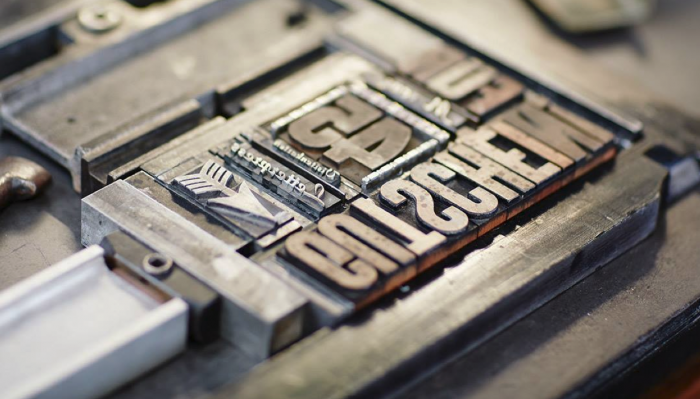
hatte die Möglichkeit mit ein paar alten (ca. 100 Jahre) Holzletter zu drucken.
Sofort verliebt in die Technik und den Look auf Munken Papier.
ICH MÖCHTE GERN MEHR ZUM THEMA »Holzdruck« WISSEN, leider ergab die Forensuche nicht viel.
Gern etwas über die Geschichte (gern auch in Deutschland) über die Technik, vielleicht eine gute Doku (youtube), was macht die Holzdruckkunst heute? usw.
Holzbuchstabenfräse im Museum der Arbeit in Hamburg:
ICH MÖCHTE GERN MEHR ZUM THEMA »Holzdruck« WISSEN, leider ergab die Forensuche nicht viel.
… was macht die Holzdruckkunst heute?
Es gibt (vom Holzschnitt abgesehen, um den es Dir ja gerade nicht geht) keine »Holzdruckkunst«. Es gibt Buchdruck, und wenn die Schriftgrade zu groß werden, um sinnvoll in Blei gegossen und gelagert werden zu können, wurden sie halt in Holz geschnitten. Holzdruck ist also keine eigene Disziplin, nicht mal eine abgrenzbare Untergruppe des Buchdruckes, Holz- und Bleibuchstaben wurden ja in derselben Druckform verwendet. Mit der Suche nach Holzdruck, Holzdruckkunst, Holzdruckerei etc. bist Du also, wenn mir das kalauern gestattet sei, immer auf dem Holzweg.
Jedenfalls hierzulande ist es so, wie Pachulke beschreibt. Meine Holzlettern kommen zum Einsatz, wenn der Zweck es fordert. Es gibt allerdings in Amerika Plakatshops, die drucken fast ausschließlich von Holzlettern, die haben gar keine anderen Schriften. Aber eine Website dazu fällt mir auf Anhieb nicht ein.
Es gibt allerdings in Amerika Plakatshops, die drucken fast ausschließlich von Holzlettern, die haben gar keine anderen Schriften.
Ich meine mich zu erinnern, daß hier letztens jemand einen Film aus einem dieser Läden gezeigt hat.
Zum Thema „Holzdruck“ sei ergänzend hinzugefügt, dass vor der Erfindung bzw. Weiterentwicklung des Buchdrucks durch Gutenberg sogenannte Blockbücher hergestellt wurden.
Von Holzstöcken gedruckte Bücher. Nicht nur die Bilder, sondern auch die Texte wurden in Holz geschnitten.
Blockbücher waren das Bindeglied zwischen den Handschriften und des Buchdrucks.
In China hatte man dieses Verfahren einige Jahrhunderte vorher entwickelt.
Es ist auch möglich, dass die Holzplatten in Teile zerschnitten, z. B. in einzelne Wörter oder Buchstaben und neu zusammengesetzt wiederverwendet wurden. So gesehen könnte hier auch eine Urform der beweglichen Letter entstanden sein.
Die Website zur Holzlettern-Sammlung von Rob Roy Kelly:
Hier ein paar Bilder von einem Workshop mit der Holzbuchstabenfräse im Museum der Arbeit in Hamburg:
Neue Holzbuchstaben kann man übrigens auch ohne Holzbuchstabenfräse herstellen. In der Holzwerkstatt der Muthesius-Kunsthochschule haben wir neulich ein komplettes Alphabet an der CNC-Fräse hergestellt.
Google mal Hamilton Woodtype Museum ...
habe mir jetzt ein paar eigene holzletter bestellt. der platzhirsch bei den üblichen gebraucht/DIY-plafformen scheint »vintage-letterpress« zu sein.
um nicht alle letter einzeln nacheinander zu drucken habe ich meist den block mit tesa fixiert. habt ihr da noch tipps? bzw. wo ich so ein vorrichtung herbekomme? (bild)
habe mir jetzt ein paar eigene holzletter bestellt. der platzhirsch bei den üblichen gebraucht/DIY-plafformen scheint »vintage-letterpress« zu sein.
Das ist nicht der Platzhirsch, sondern es sind erbarmungslose Geschäftemacher, die jede Letter einzeln völlig überteuert verkaufen, damit natürlich komplette Sätze auseinanderreißen und somit alles tun, um den Druck mit Holzlettern in Zukunft noch schwerer zu machen.
um nicht alle letter einzeln nacheinander zu drucken habe ich meist den block mit tesa fixiert. habt ihr da noch tipps? bzw. wo ich so ein vorrichtung herbekomme?
Empfehlenswert wäre ein Praktikum bei jemanden, der Ahnung davon hat und sowas macht. Sonst wirst du mit der Fragestellerei hier gar nicht mehr fertig ... Als Minimum wäre zumindest mal der Besuch bei einem Buchdrucker, einem Buchdruckmuseum oder einer Buchdruckwerkstatt anzuraten oder auch ein Blick in ein diesbezügliches Fachbuch beispielsweise
Hochdruck von Hans J. Wolfsturm und Hermann Burkhardt (1997).
Vom Platzhirsch habe ich mal eine fachkundige Antwort erhalten: Als ich ihn fragte, ob bei dem A einer seiner angebotenen Leichenteile zufällig De Little York auf Ober- und/oder Unterseite zu lesen ist, meinte er: »Ja, die machen tolle Schriften, oder?« (Anmerkung: "die" machen seit fast 20 Jahren keine Schriften mehr und De Little selbst hat bis zuletzt alleine gearbeitet ... und ist dieses Jahr leider verstorben)